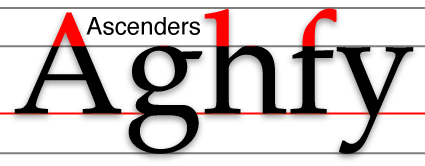
升部(Ascenders)
导语在西文字体排印学中,升部(Ascenders)是指一个字体的字母中向上超过主线笔画的部分,也就是比x字高还要高的部分,是字体设计中一个重要的组成部分。升部,和降部笔画可以增强单词的识别率。因此,英国的高速公路标识放弃采用一律大写字母的做法,增强可读性
在西文字体排印学中,升部(Ascenders)是指一个字体的字母中向上超过主线笔画的部分,也就是比x字高还要高的部分,是字体设计中一个重要的组成部分。
升部,和降部笔画可以增强单词的识别率。因此,英国的高速公路标识放弃采用一律大写字母的做法,增强可读性。
图:红色部分即为升部